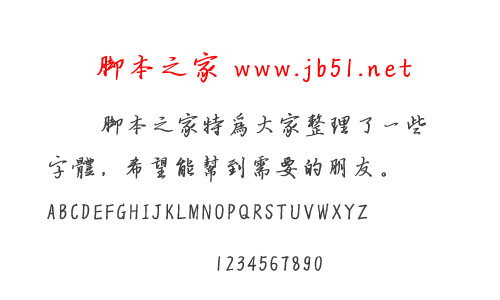
漢儀寒石粗體繁字體是一款由漢儀字庫(kù)推出的粗體中文藝術(shù)字體,該字體屬于手寫(xiě)體中的硬筆書(shū)法,具有現(xiàn)代感的外觀和清晰易讀的效果,線條粗細(xì)適中,整體風(fēng)格非常出色,并且字庫(kù)完整,可用于藝術(shù)設(shè)計(jì)、包裝印刷、簽名設(shè)計(jì)、圖形設(shè)計(jì)等領(lǐng)域,歡迎有需要的朋友們前來(lái)下載使用。